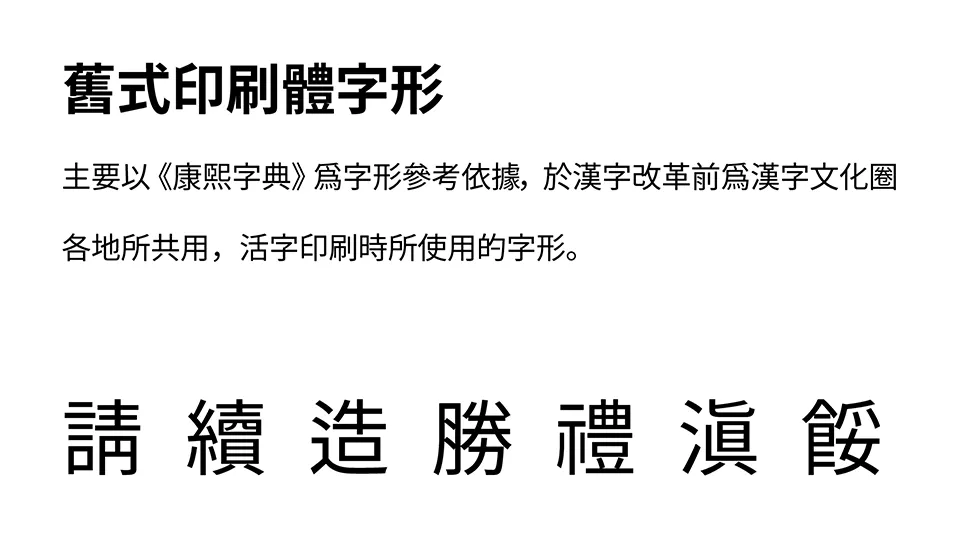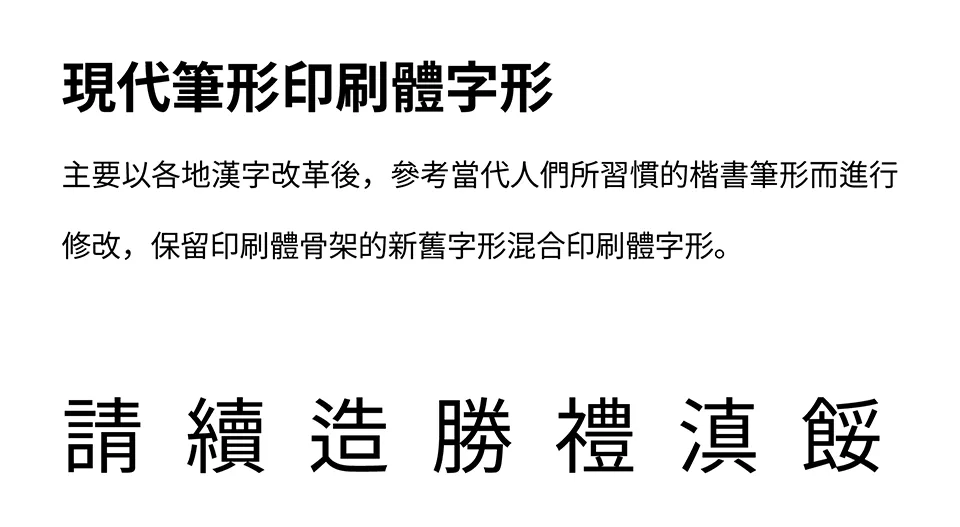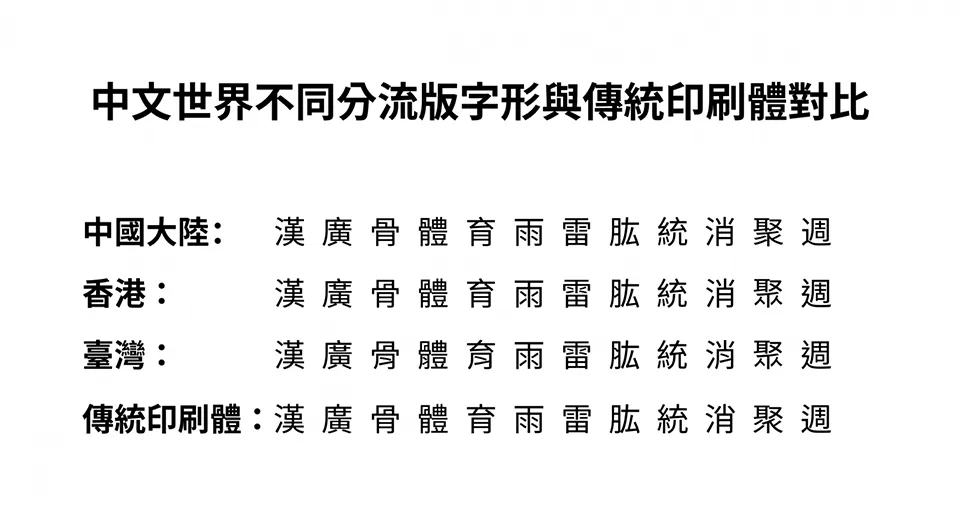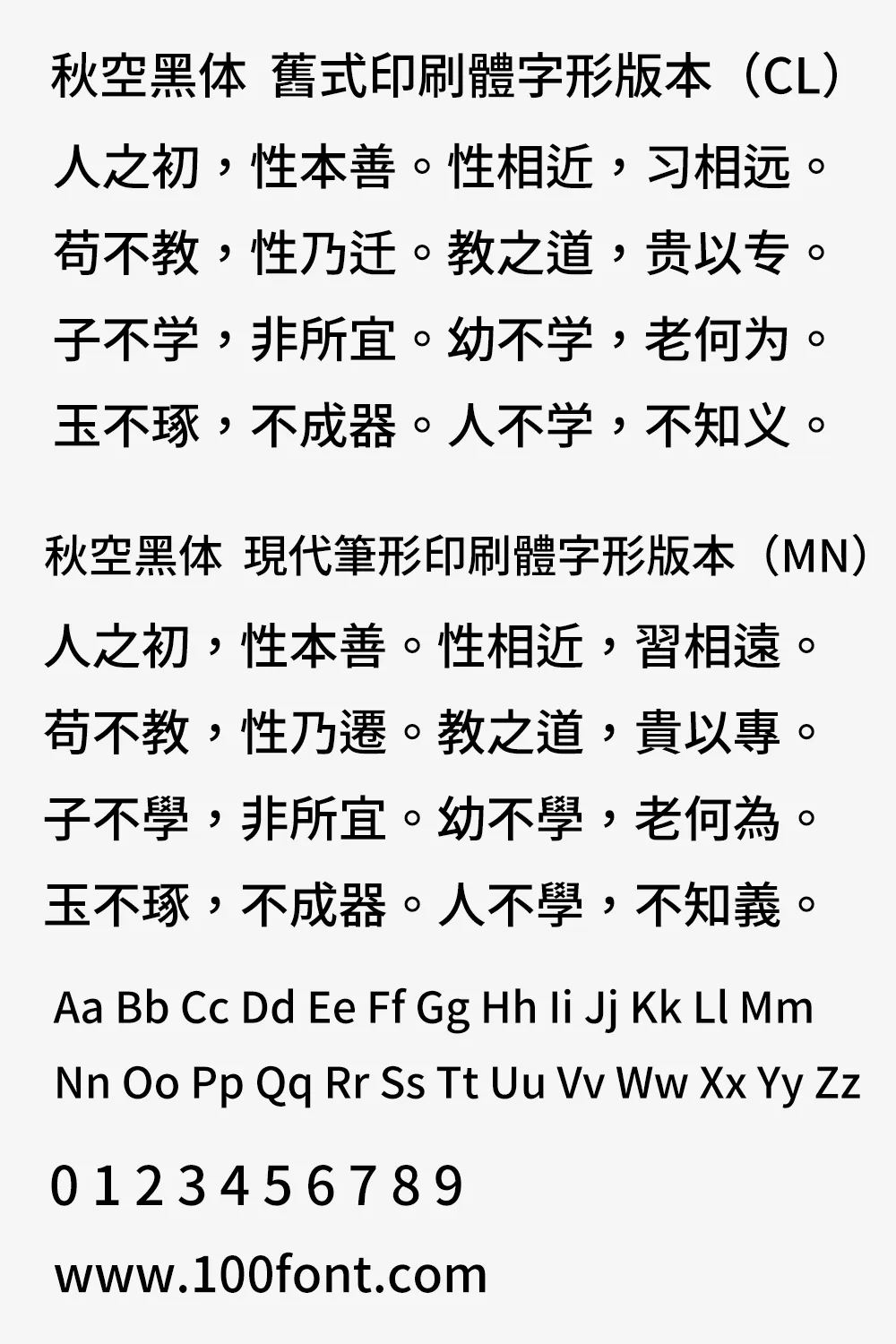
秋空黑體是一款基於思源黑體,同時整合異體字選擇器功能的中文印刷體風格字體家族項目。根據字圖映像所指定的默認字圖字形風格的不同,分為以下兩個分流版本。
舊式印刷體字形版本(CL):所使用的默認字圖字形為各地漢字改革以前慣常使用的活字印刷字形,其字形標明基準大致與「いわゆる康熙字典體」相同。因簡體字修改進程仍未完善及簡體字用戶可能並不習慣舊字形考慮下,目前僅推薦於傳統漢字的場景下使用。
現代筆形印刷體字形版本(MN):所使用的默認字圖字形為兼顧當代慣用筆形及保留印刷體骨架的新舊字形混合印刷體風格字形。如有兼顧簡體字使用場景的需求推薦使用該分流版本,但仍建議主要於傳統漢字的場景下使用。
注:無論是CL版還是MN版都可以利用字體整合的異體字選擇器功能選擇字符的其他字形,簡單來說卽使用MN版時亦可透過異體字選擇器指定CL版本默認字圖為該字符的指定字形字樣。
注:作為一款兼顧純文本異體字排版特殊用途的字體,於日常顯示用途或其他場景時可能會因「源規格分離原則」導致風格不一致的情況出現,請在具有需要統一風格的需求或不滿意部分字符的字形時多多善用本字體所整合的異體字選擇器功能、使用源規格分離分別編碼的字符或基於本項目進行進一步的改作。
字印刷體風格:二戰後漢字圈各地因各種原因,基本上都在文字改革的浪潮中將手寫體及印刷體進行統一化處理,而其初衷乃以縮小其兩者之間的字形差異而減少在漢字教學上產生的不便。在修訂參考字形方面多數的處理方式是將活字鉛字的慣用字形修改成貼合楷書慣用字形,而少數則是將手寫體向印刷體字形靠攏。
但與日本僅將字形調整為傳統楷書字樣而保留傳統印刷體的筆畫處理方式不同的是,大中華地區各地在進行漢字改革時無一例外都有將楷書筆畫規則引入到印刷體當中,而其造成的影響是文本排版文字跳動感較大、字符重心不穩、可閱讀性差等諸多問題——而在眾多字形參考資料/標準當中以臺灣教育部所訂立的「國字標準字體」最為尤甚。
因此,在一些調整過後的參考字形並非強制性標準的地區中,出現了不少拒絕採納的聲音,以印刷界為代表的各業界仍然繼續沿用原先的印刷體字形字樣。雖然今日不少字形為了順應當代民眾的用字習慣而進行了調整,但大體上依舊保留著印刷體骨架而非參考字形那般將手寫體特徵無節制地套入到印刷體當中。
而選擇繼續使用帶有印刷體骨架的字形的字體而非根據標準使用楷化字形所帶來的好處是文本排版整齊,跳動感較少,文字辨識性較強,更加適合用於印刷場合及電子熒幕顯示等用途。
異體字選擇器:目前絕大部分面向中文使用者的字體基本都會指定其中的一個字形為該字符的唯一字形,部分字符的字形可能並不是使用者所希望使用的字形,而且因各種原因普遍都不會搭載異體字選擇器這個已經普遍在日語字體實裝的功能。
這樣的做法是,在需要顯示單一字符的不同印刷體字形寫法的場合時亦顯得略微不便,這一不便在為了風格整齊劃一而進行統一化處理的字體十分明顯——難以透過字形分辨不同編碼的字符,這對於希望可以透過使用或分辨「源規格分離原則」分別編碼的同字不同字形(或正俗字)字符需求中尤為致命。
而卽便沒有進行統一化處理亦難以透過純文本的方式進行顯示某些統一編碼但印刷體當中有著不同字形的寫法,通常很多人在面臨類似的問題時多數會選擇搭配不同字體使用,但弊端較為明顯的是無法在不支持多字體編排的場合中使用。
故本項目決定實裝已經在日語社區使用有一段時間的異體字選擇器,其將可以有效解決純文本異體字編排難的問題。卽透過這一功能使不用切換字體就可以達到在純文本的場景下同時顯示同編碼字符的不同字形,同時亦能透過使用異體字選擇器滿足部分使用者有對特定字符有指定字形的需求。